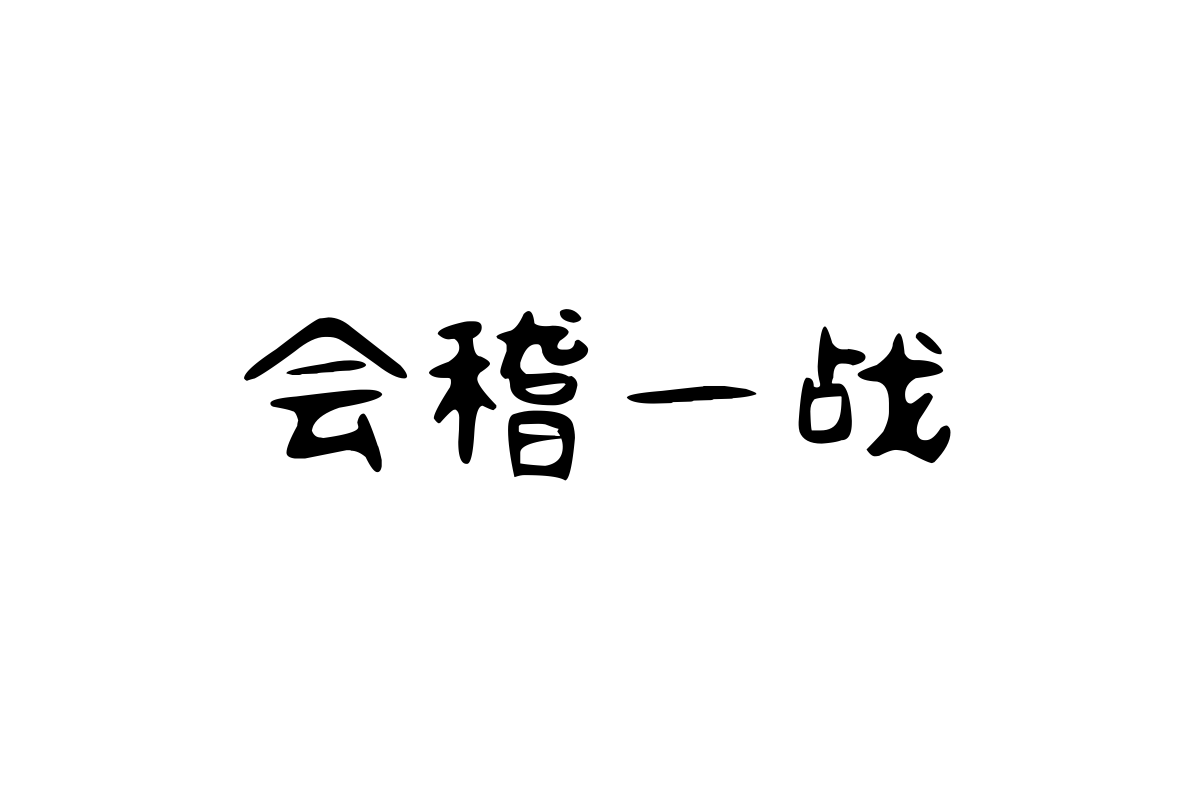
汉仪新蒂手指画字体是一款创意独特的手写字体。这款字体的设计灵感来源于手指在纸上的绘画过程,通过模仿手指在纸上的滑动、弯曲和勾勒,形成了独特的笔画和形状。这种设计使得这款字体既有手写的感觉,又具有现代艺术的气息。
汉仪新蒂手指画字体的特点在于其独特的笔画和形状。每个字符都经过精心设计,以模拟手指在纸上的绘制过程。这使得这款字体既有手写的流畅感,又具有现代艺术的美感。
此外,汉仪新蒂手指画字体还具有易读性和可识别性。由于其独特的笔画和形状,这款字体在阅读时不会显得过于复杂或难以理解。同时,它的可识别性也很高,无论是用于印刷还是电子显示,都能保持清晰可读。
总的来说,汉仪新蒂手指画字体是一款既具有艺术气息又实用的手写字体。它不仅适合用于书籍、杂志、海报等印刷品,也适合用于网页设计、手机应用等电子显示领域。